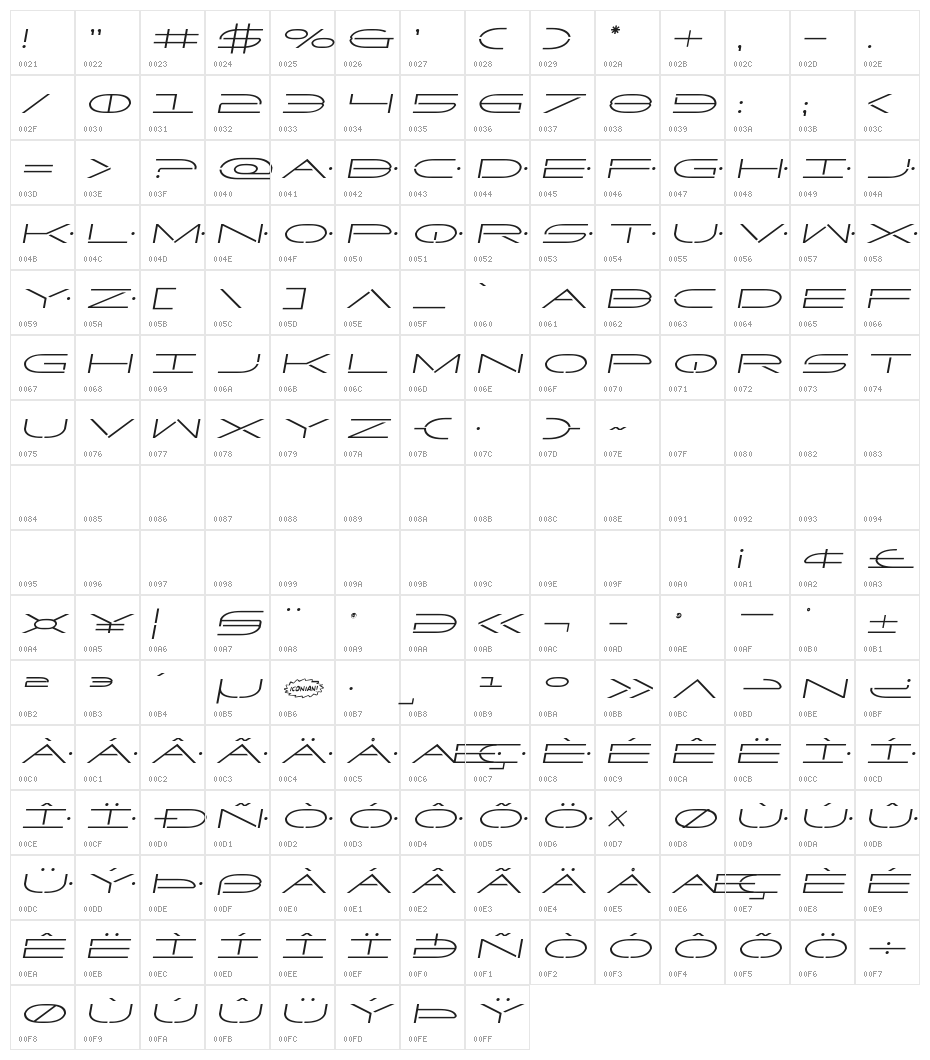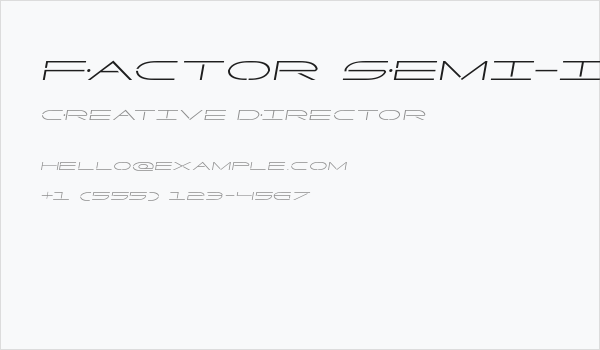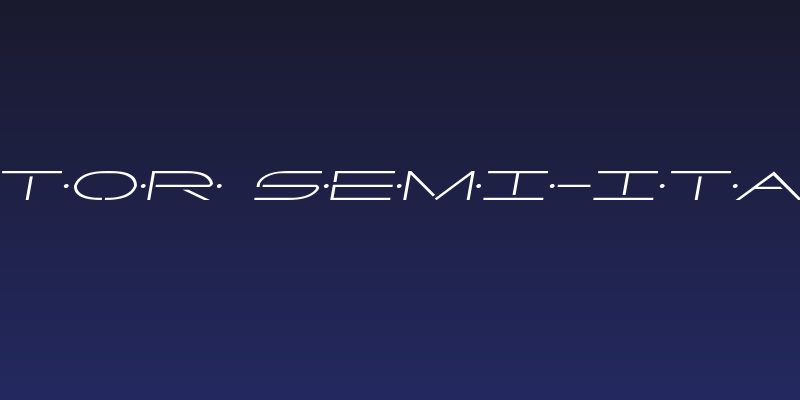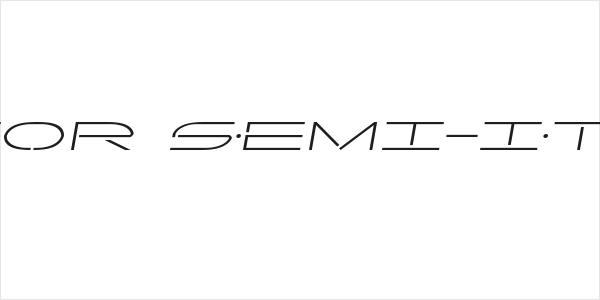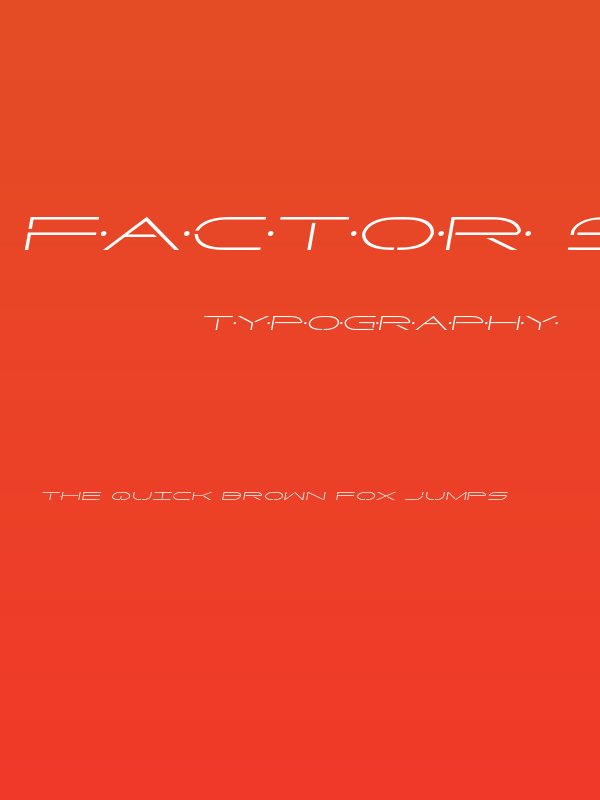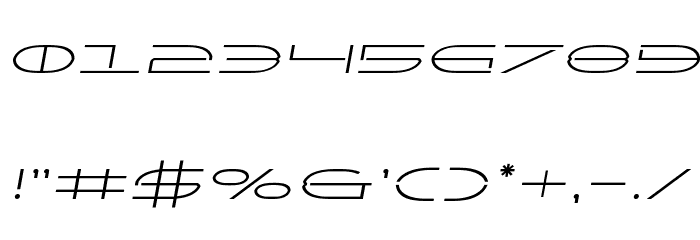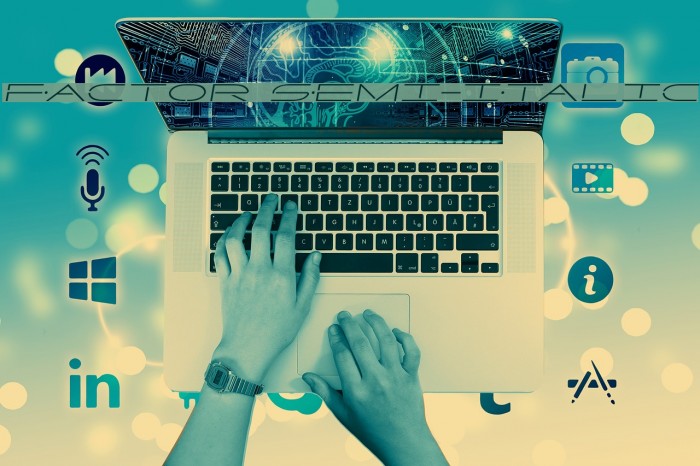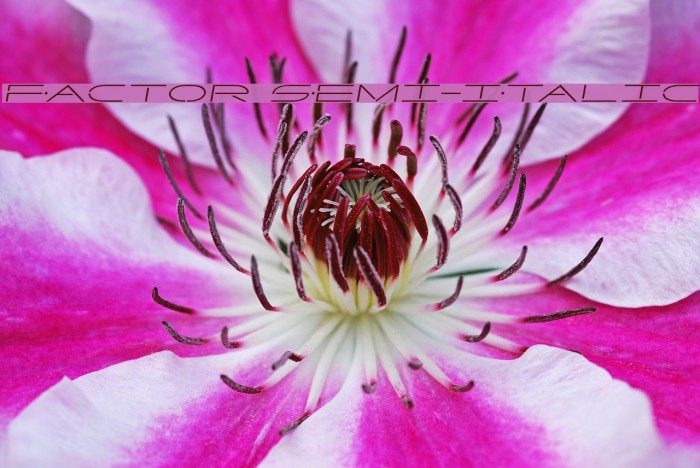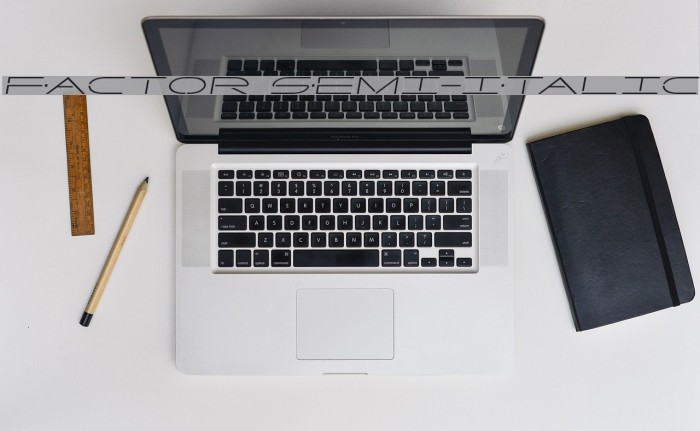
Factor Semi-Italic Font
| Gesamtstil | Futuristic, Geometric |
| Anwendungsfall | Headlines, Logos, Branding |
| Vorgeschlagene Projekte | Ideal for technology branding, sci-fi themed designs, modern advertising, and innovative product packaging. |